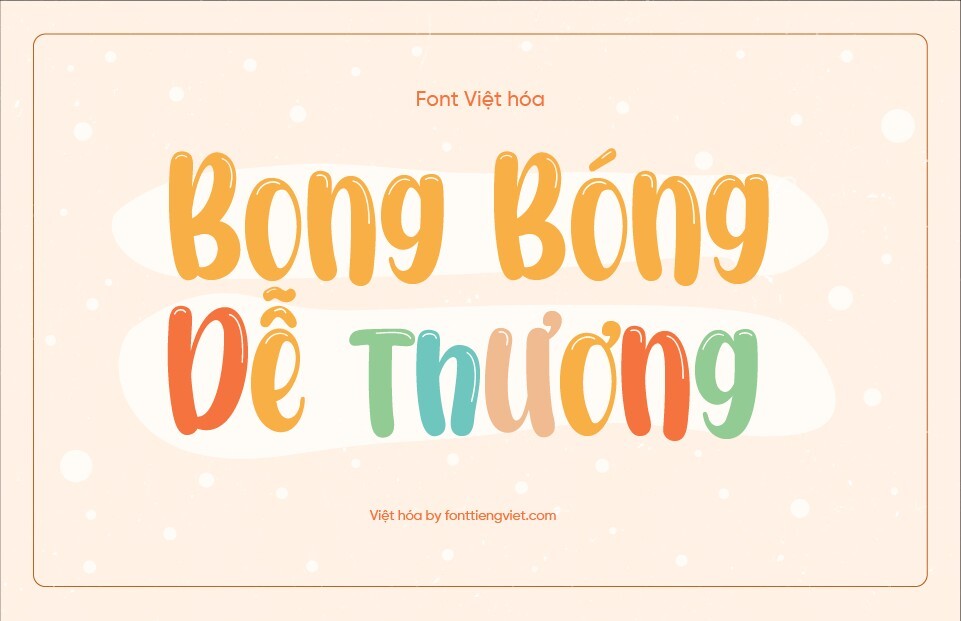
Font Việt hóa 1FTV VIP Bubble Shine – Font bong bóng
Font Việt hóa 1FTV VIP Bubble Shine – Font bong bóng cho thiết kế sáng tạo
Giới thiệu về Font Việt hóa 1FTV VIP Bubble Shine – Font bong bóng
Trong thế giới đồ họa hiện đại, việc tìm kiếm một bộ Font Miễn Phí mang phong cách trẻ trung và vui nhộn luôn là ưu tiên hàng đầu của các bạn học sinh và giáo viên. Font Việt hóa 1FTV VIP Bubble Shine – Font bong bóng chính là lựa chọn hoàn hảo để thổi hồn vào các dự án thiết kế học đường. Với những đường nét tròn trịa, căng mọng như những quả bong bóng, phông chữ này gợi lên cảm giác thân thiện và đầy sức sống. Đặc biệt, phiên bản Việt hóa hoàn chỉnh giúp người dùng dễ dàng thể hiện các nội dung tiếng Việt mà không lo lỗi dấu hay thiếu ký tự cần thiết.
Ưu điểm nổi bật của Font Việt hóa 1FTV VIP Bubble Shine – Font bong bóng
Phong cách bong bóng độc đáo
Đúng như tên gọi, bộ chữ sở hữu hiệu ứng đổ bóng tinh tế, tạo cảm giác 3D chân thực như những khối bong bóng đang tỏa sáng dưới ánh mặt trời. Điều này giúp các tiêu đề bài thuyết trình hay bìa báo tường trở nên nổi bật và thu hút thị giác ngay lập tức. Cấu trúc chữ cái rõ ràng nhưng vẫn giữ được sự mềm mại, rất phù hợp cho các không gian sư phạm sáng tạo.
Ứng dụng đa dạng trong học tập
Bạn có thể sử dụng bộ font này để làm thiệp chúc mừng, thiết kế logo cho câu lạc bộ hoặc trang trí các góc học tập tại lớp. Sự linh hoạt của nó cho phép kết hợp tốt với nhiều màu sắc rực rỡ, giúp khơi gợi cảm hứng học tập và làm việc cho cả giáo viên lẫn các em học sinh.